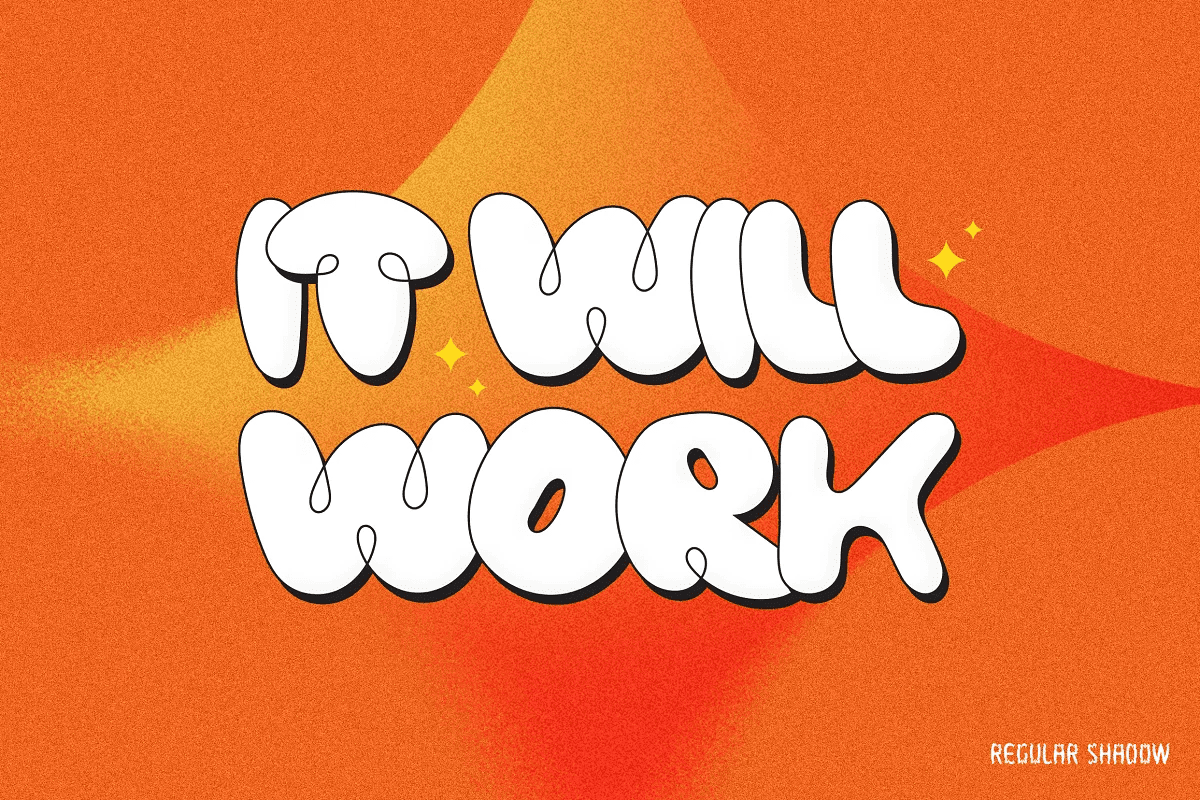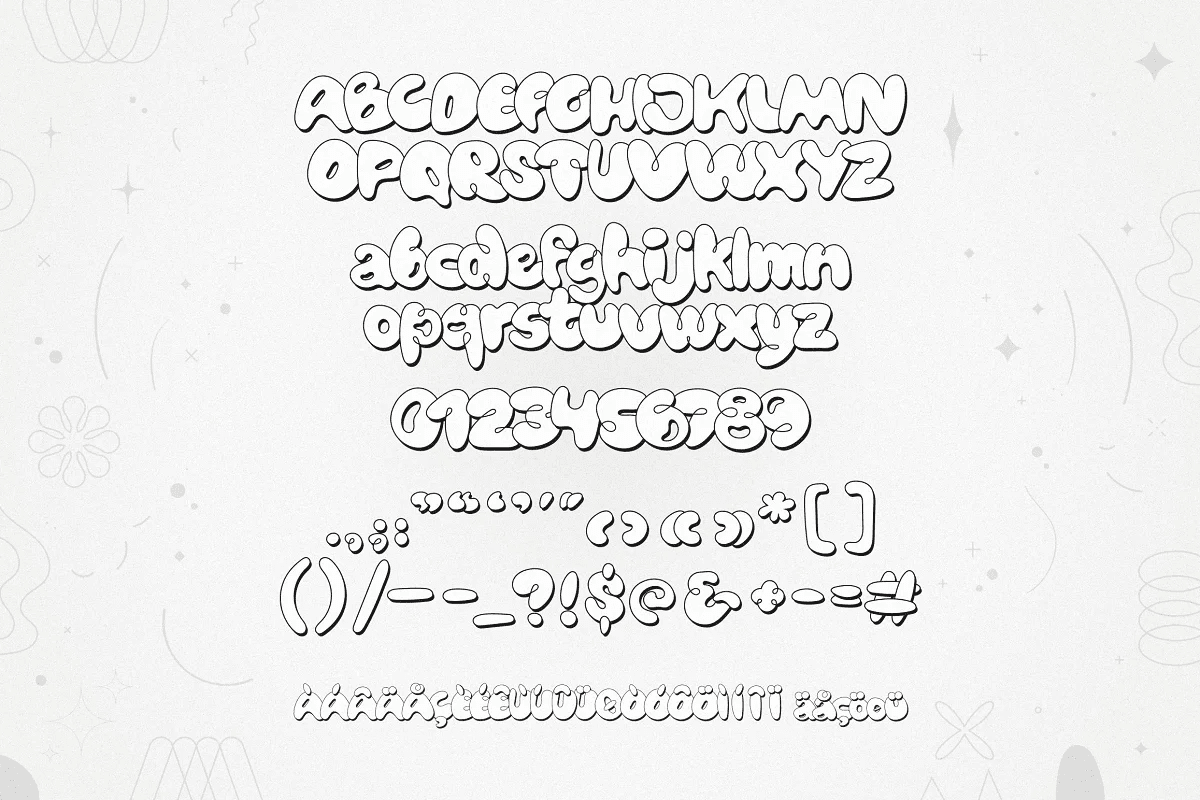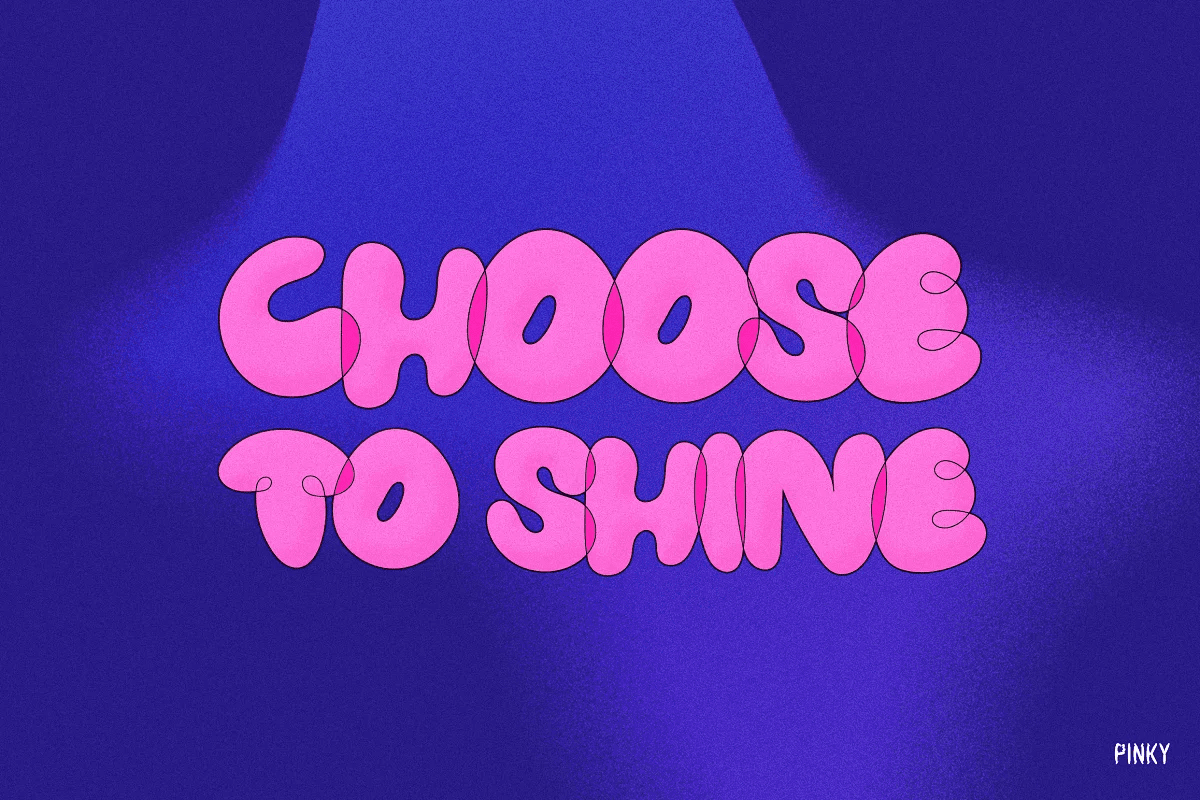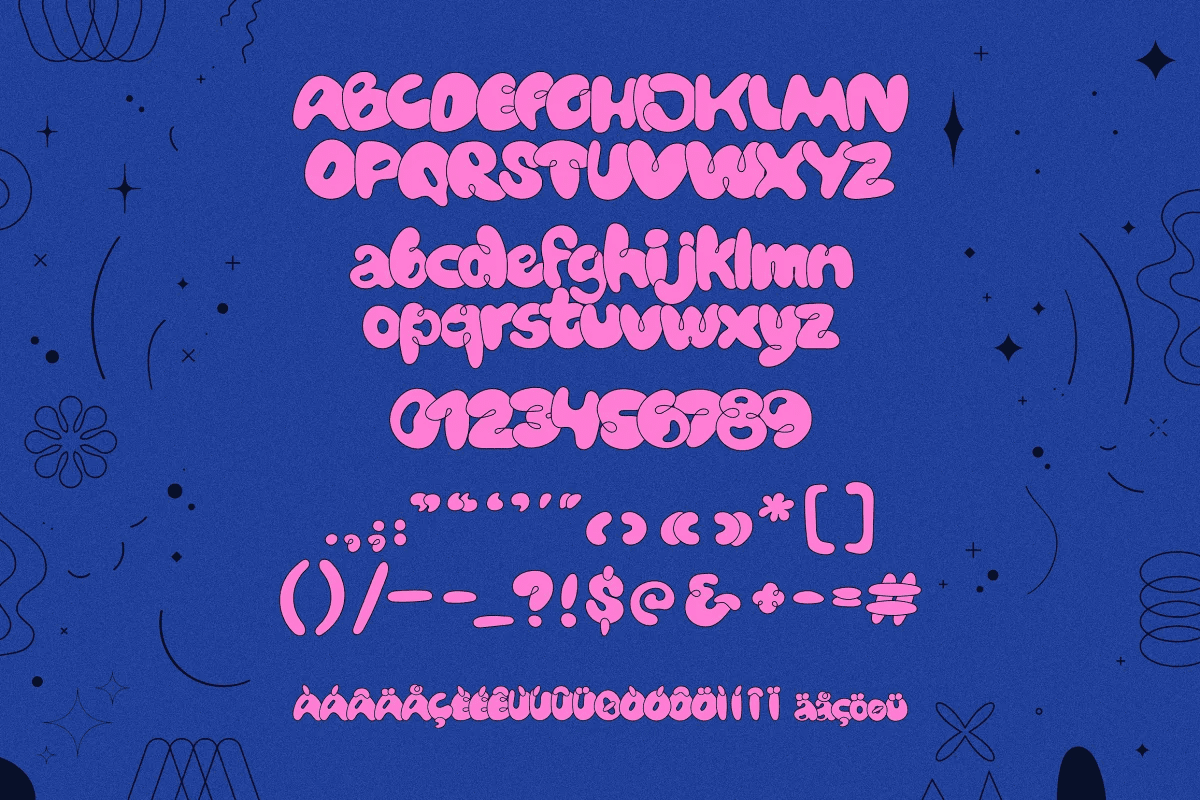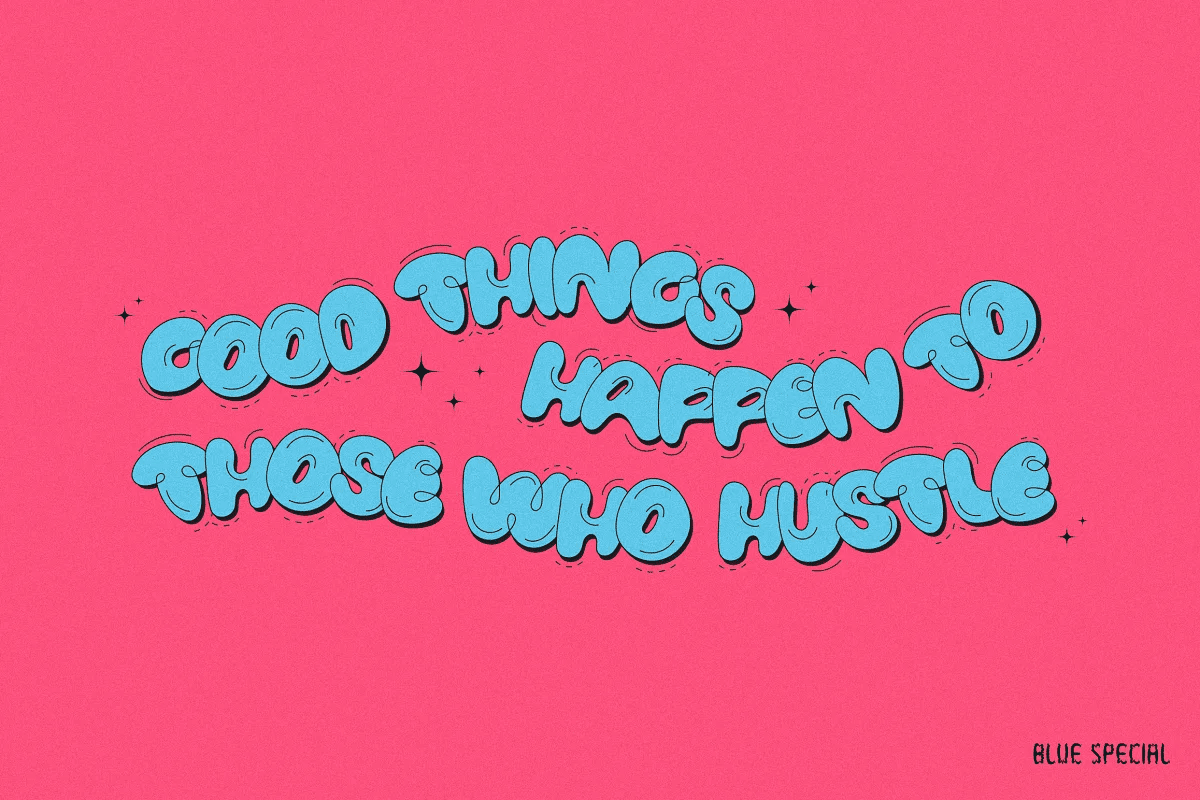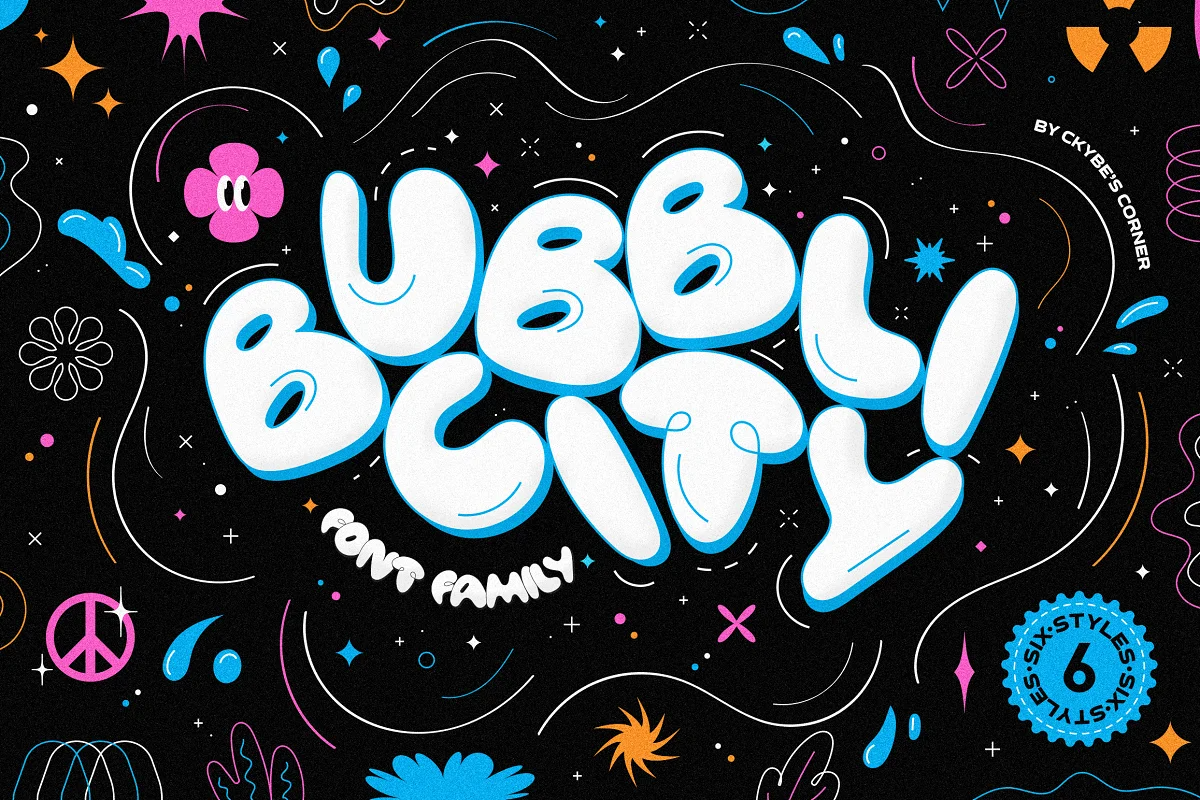
Giới thiệu Bubblicity – Họ phông chữ vui tươi với 6 kiểu bao gồm cả kiểu màu. Phông chữ bong bóng này được tạo ra với tình yêu ngọt ngào của thời kỳ những năm 90 và 2000 và một chút cảm hứng với graffiti đường phố kết hợp với các yếu tố đường nét bay xung quanh nó. Hoàn hảo cho áp phích, bài đăng, lời mời và các nội dung nghệ thuật khác. Ngoài ra bạn có thể sử dụng phông chữ làm logo. Bạn có thể chơi với khoảng cách vì các chữ cái chồng lên nhau một cách hoàn hảo. Cố gắng sử dụng nhiều tùy chọn hòa trộn và thay đổi màu sắc/độ bão hòa. Rất nhiều cơ hội với các tùy chọn khác như vát và chạm nổi.